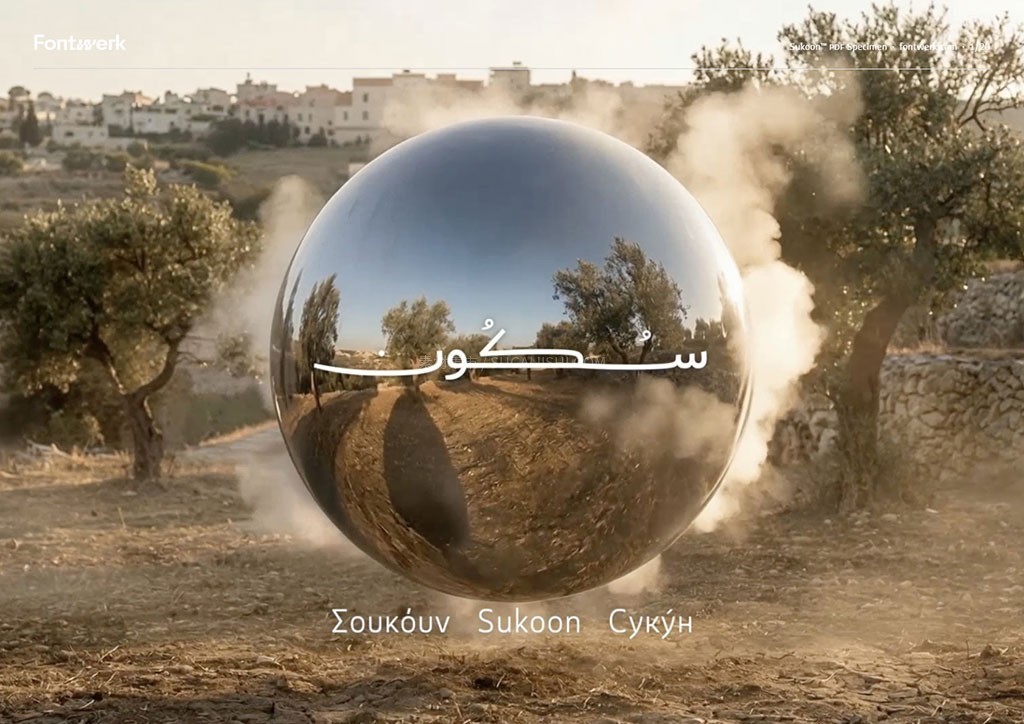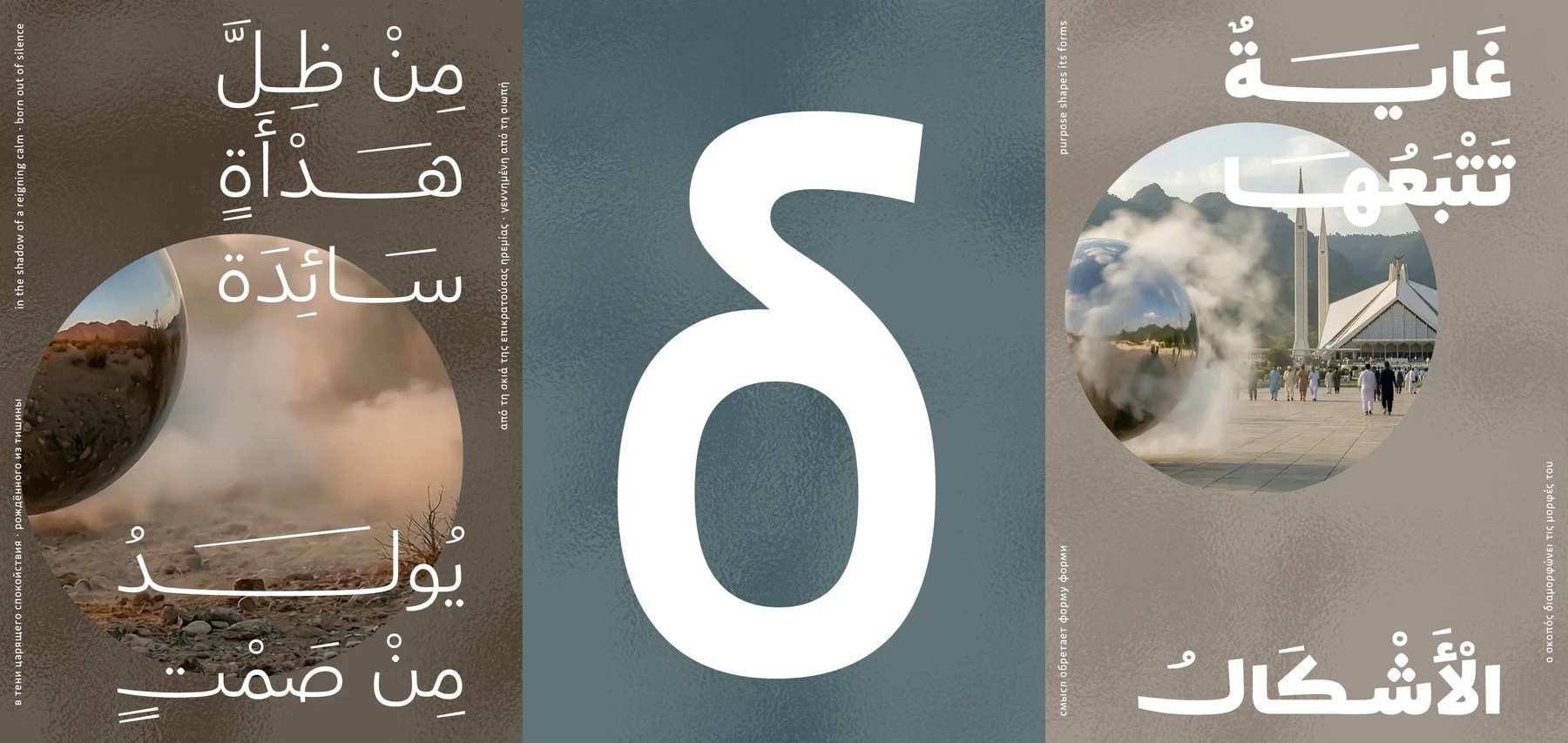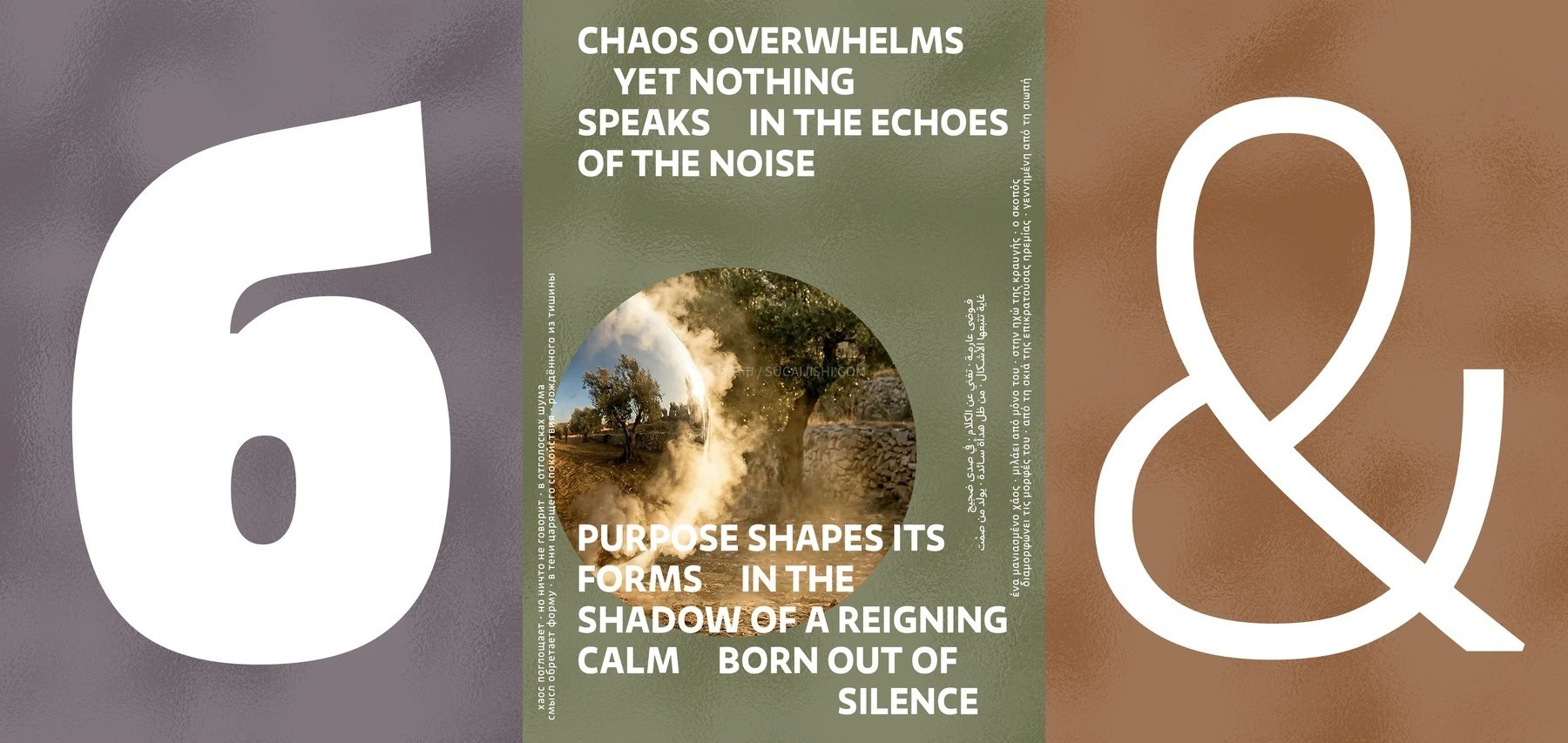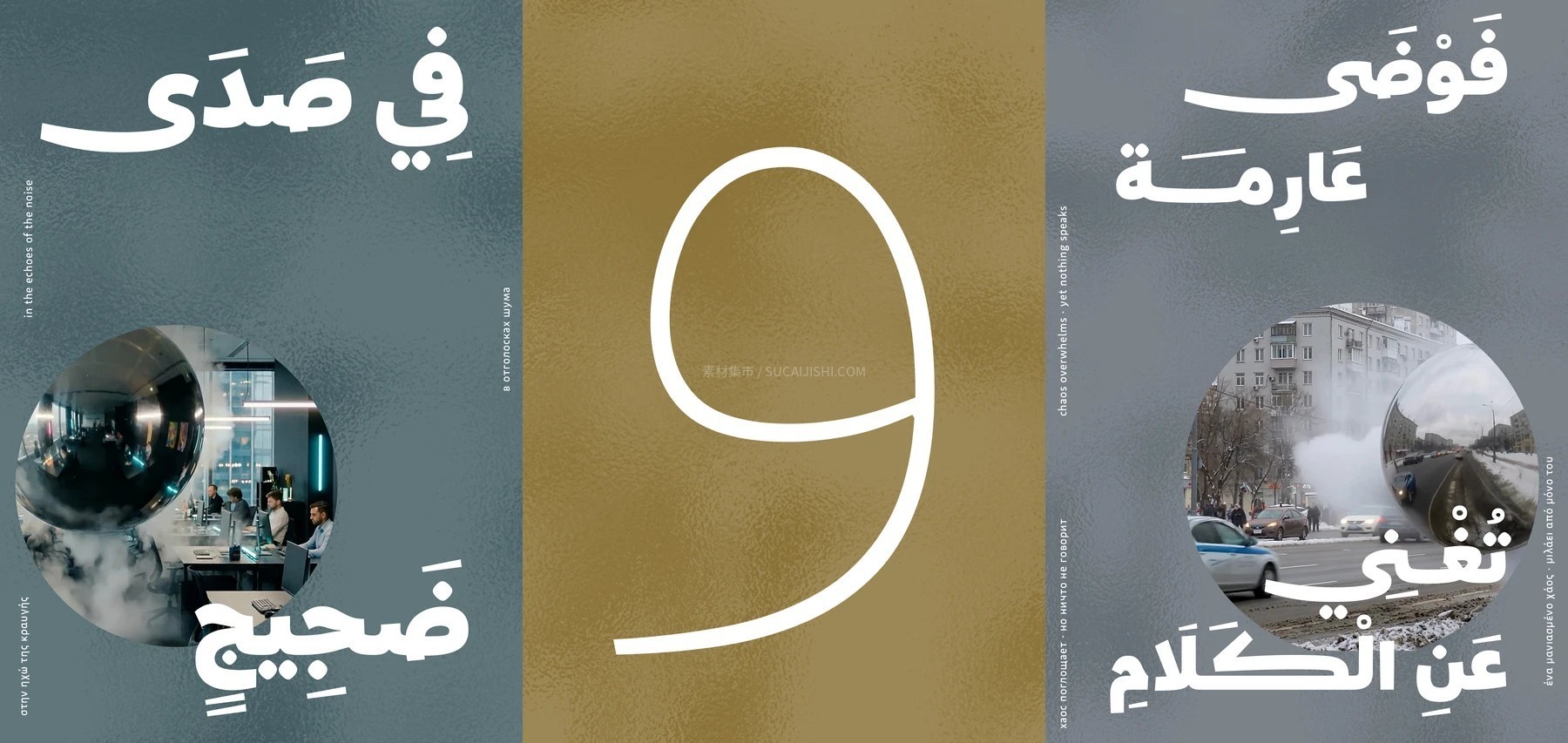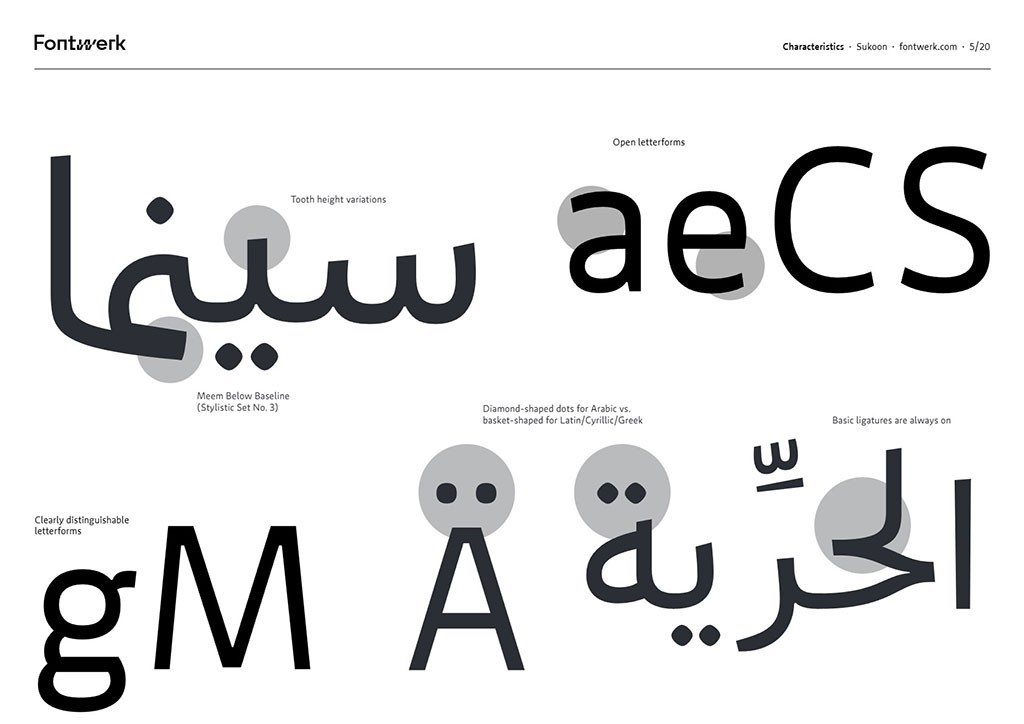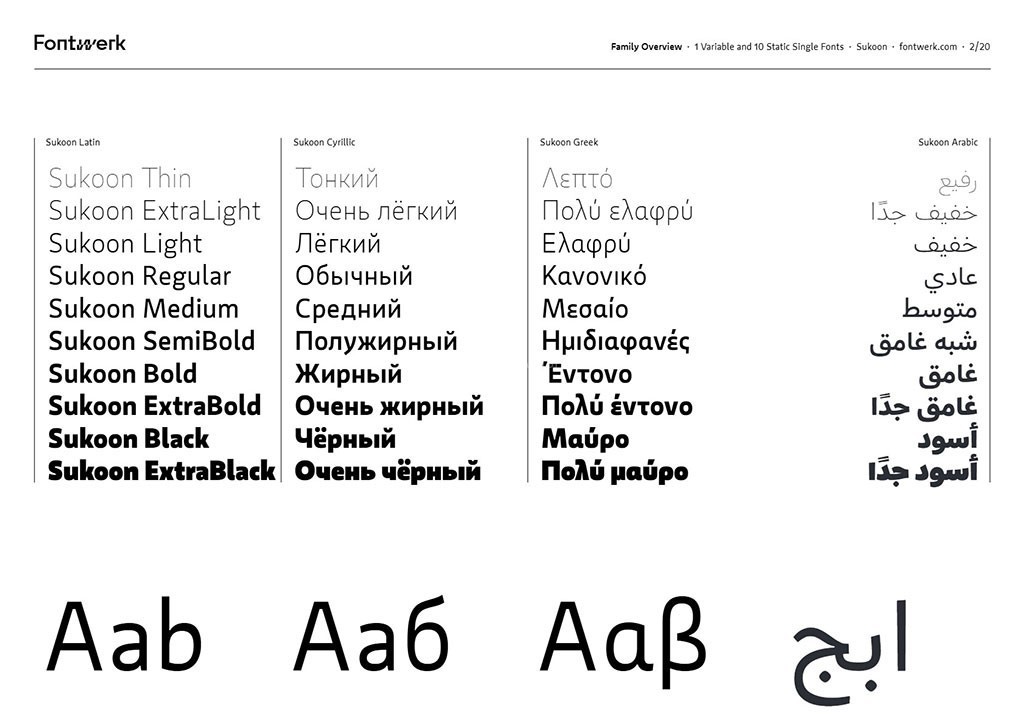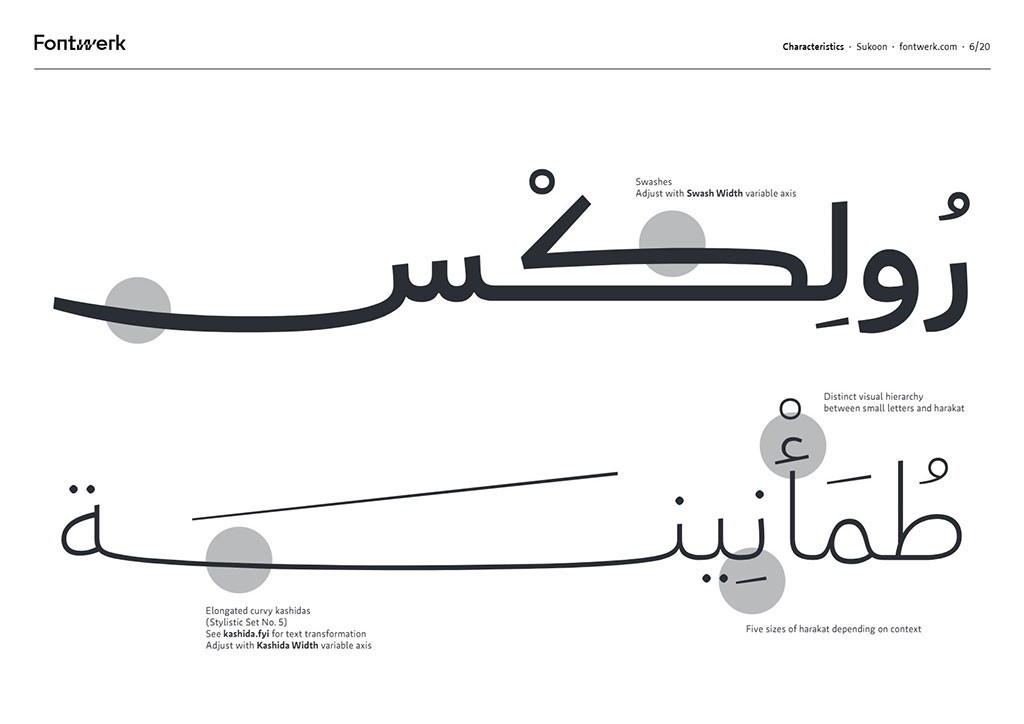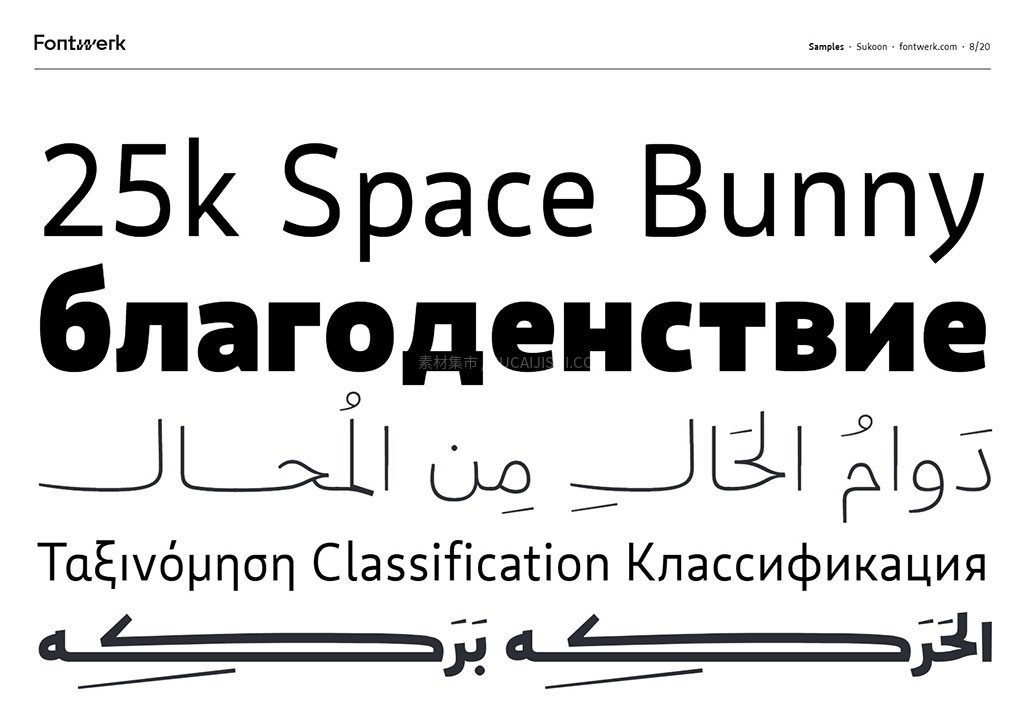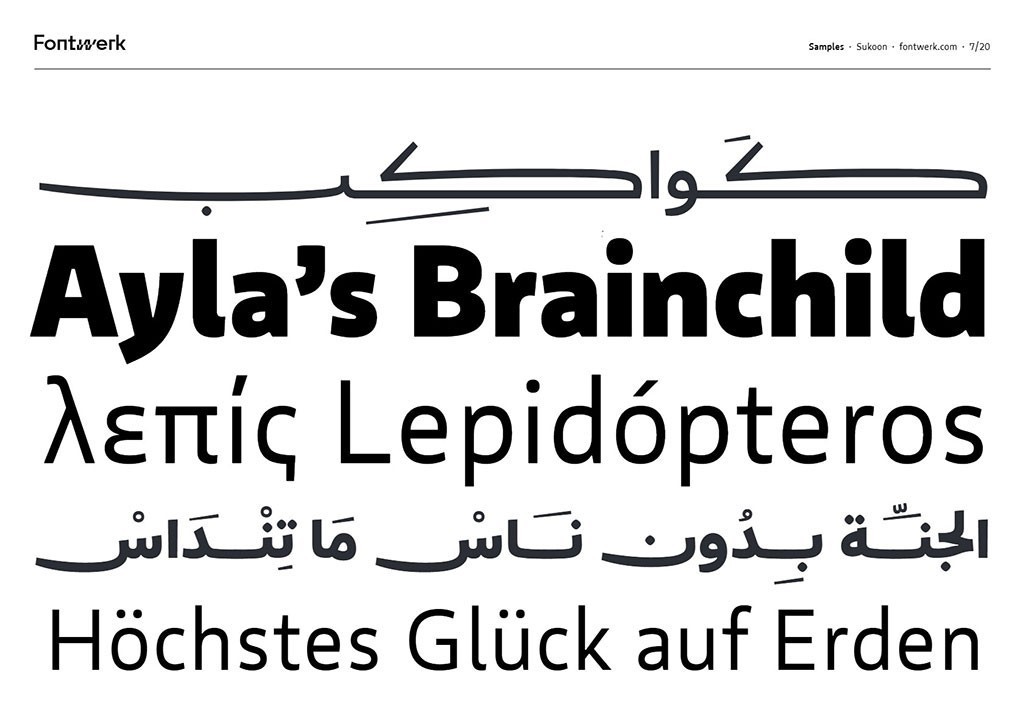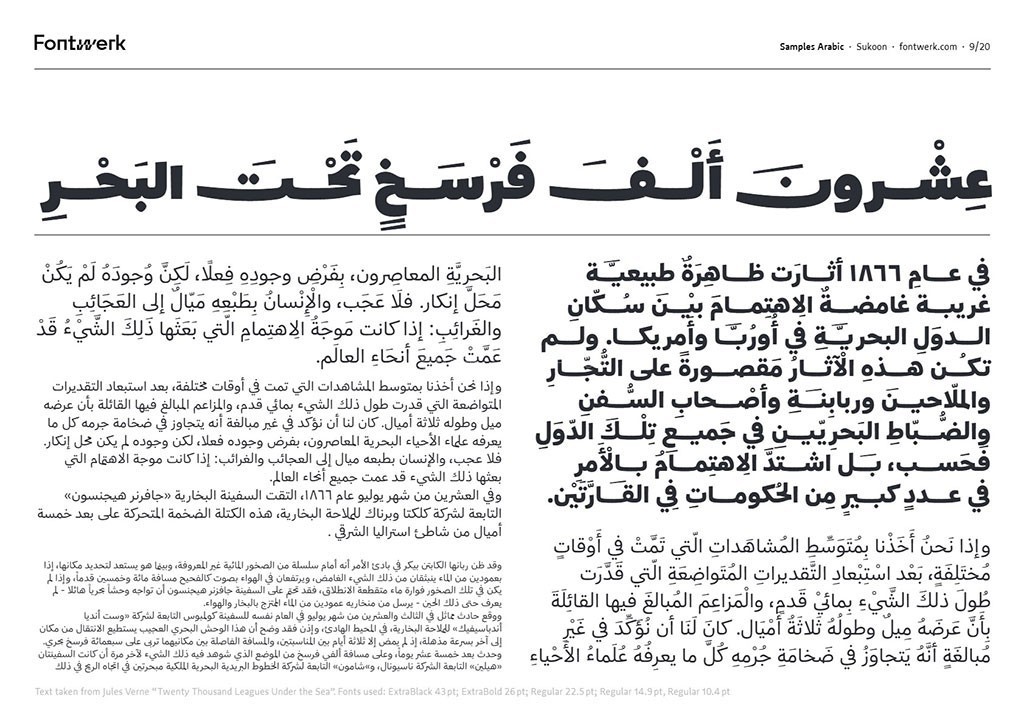
Sukoon 多语言字体家族
Sukoon 是一款包含拉丁字母、阿拉伯字母、西里尔字母和希腊字母的20种样式及可变字体。由设计师 Yanone 在极度宁静中创作,完美诠释了静谧、清晰与内心的平静。如同阿拉伯语中的同名符号,这款字体能在视觉语流中带来片刻的静默与安宁,传递节俭、感恩与自然深厚联系的精神共鸣。